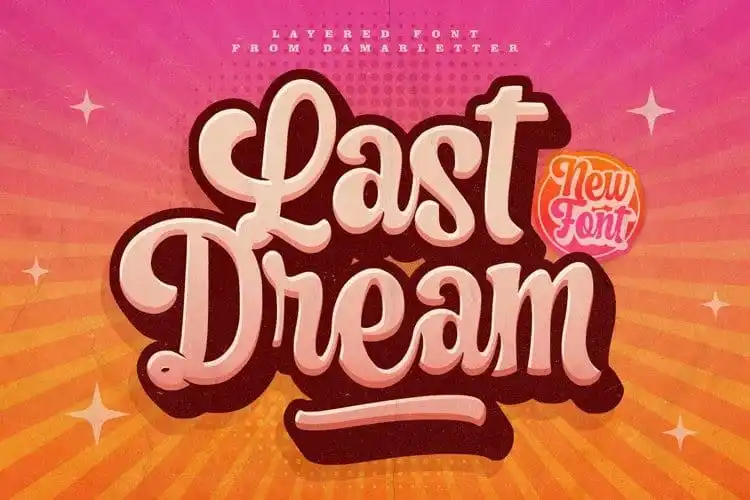
Last Dream Script Font – Download Grátis
A fonte ‘Last Dream Script Font’ foi criada para designers que buscam uma solução elegante e nostálgica. Inspirada nos estilos vintage e retro, ela oferece um toque de sofisticação clássica aos designs modernos. Last Dream é composta por uma fonte estilo layered, com versões normais e extruded. Este projeto foi cuidadosamente desenvolvido para permitir que alternativas contextualizadas do tipo OTF criem um efeito em fatias, oferecendo ao designer muitas possibilidades estilísticas. Ideal para aplicar em logotipos, gráficos de texto ou qualquer design que deseje adicionar um charme vintage sem perder sua essência moderna. Esta fonte foi feita para aqueles que valorizam a mistura perfeita entre o passado e o presente.